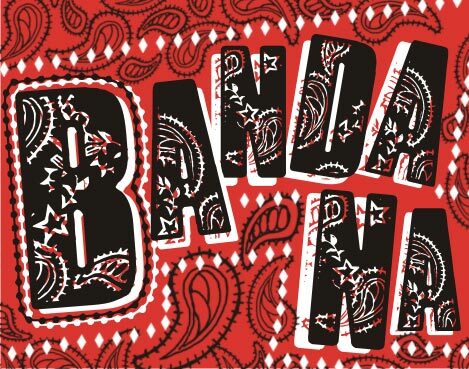
VTKS Bandana di Douglas Vitkauskas è un font display gratuito in stile western, costruito attorno a ornamenti paisley e lettere con bordi cuciti. Le maiuscole sembrano ritagliate da un tessuto stampato: forme piene e decise, delineate da tratteggi che ricordano le cuciture e riempite con piccoli motivi floreali, stelle e gocce, mantenendo il richiamo cowboy senza risultare eccessivo.
Si adatta perfettamente a manifesti di rodeo, volantini per festival country, packaging per barbecue, insegne rustiche o inviti per feste a tema, dove sono le lettere stesse a fare da decorazione. Essendo un font gratuito, è ideale anche per brevi titoli, copertine e monogrammi, soprattutto quando vuoi che quel gusto tipico della bandana comunichi subito il concetto.